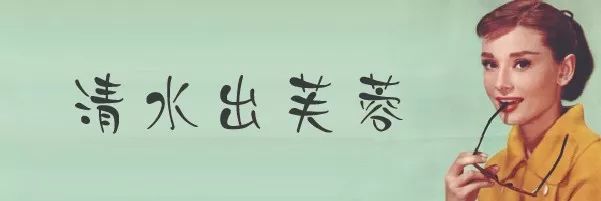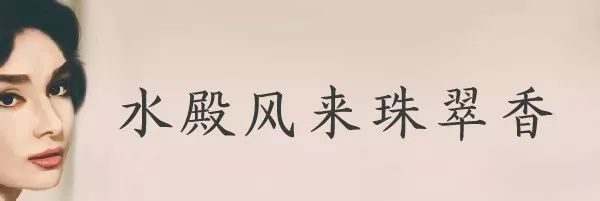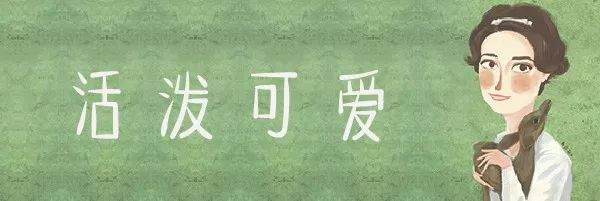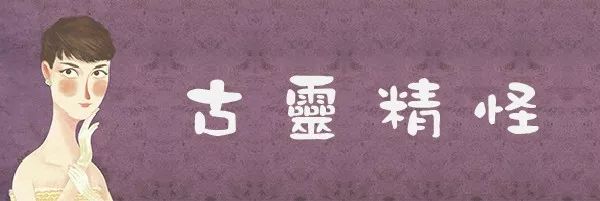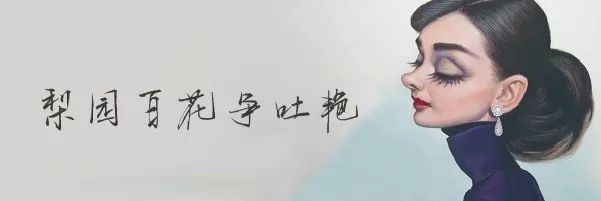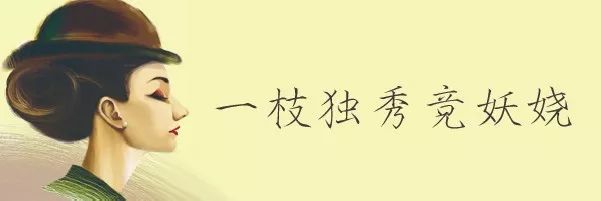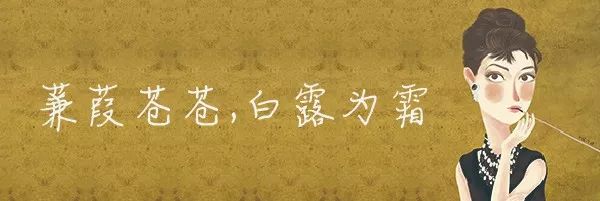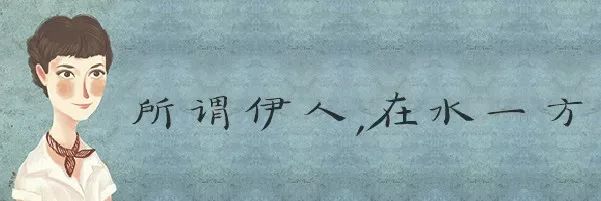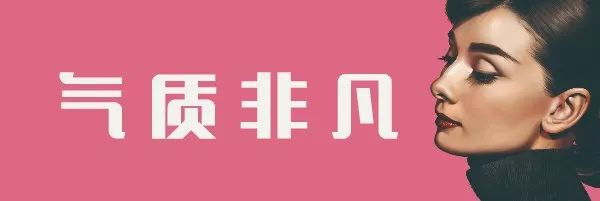
女王节花样字体大全,分享适合女王节的14款字体
专属节日×女性字体
所以小编从美丽、优雅、可爱、温柔…这些超多女性字体中精选了14款字体给大家~让花样字体,专属宠你!
经典装饰女性字体
汉仪黛玉体
汉仪秀英体
新派标题女性字体
汉仪铸字美心体
汉仪瑞意宋
诗情画意女性字体
方正楷体简
汉仪新蒂唐朝体
优雅正文女性字体
汉仪润圆
汉仪全唐诗
可爱休闲女性字体
汉仪喵魂体
华康墨字体
潇洒帅气女性字体
汉仪春然手书
华康瘦金体
温婉手写女性字体
汉仪晨妹子
汉仪李政恩小楷
每款字体都有自己的专属特性,
这么多款性格的女性字体,